英文字体转换器:免费一键转换用它就够了!
想要快速生成特色英文字体么?想要拥有可以让你挑花眼的英文字体库么?在你的设计行业中,很多时候需要英文字体来给画面增添一些新鲜感和美感,想要找到合适的英文字体是一个耗时耗力的过程,还有可能设计版权风险。我给大家找到了一款功能齐全、字体丰富、使用无门槛的在线工具——字由,它作为专业的字体管理工具,能在线一键转换英文字体,一键应用到各大设计软件,无需安装其他辅助工具。不仅如此,字由还拥有庞大的字体模板资源,覆盖多种风格,大大提升你的设计效率,是不可或获取的字体神器!
一、字由的核心优势有哪些?
1.一键应用字体:无门槛操作
通过字由客户端可实现在 PS、AI、XD、Figma、Sketch 等设计软件中一键应用字体,无需下载,安装字体包,即可完成字体应用,省去了字体查找,下载,安装的麻烦。只需要在众多字体模板中选择一款你喜欢的英文字体,就可以实现一键转换新手小白也能一秒掌握。
2.多风格字体覆盖:适配全场景
字由客户端集成了 5000+ 精选字体,1000+ 字体厂商公开授权免费商用字体,涵盖书法体、创意字体、宋体、黑体、手写体、彩色字体等多种字体类型,可匹配多种设计场景,满足不同的设计需求。而且字体会定期更新,紧跟当前设计趋势,避免风格过时。
二、字由如何实现字体转换?
1.字体模板一键转换
进入字由官网,在上方工具栏点击[全部字体],在字体类型里筛选出英文字体,一般我会直接选择“Display”“Handwriting”这种英文标题的类型,或者可以在[展示类别]里直接筛选英文。
在众多英文字体模板中,选择你喜欢的一款字体。
在字体详情页面,输入文字,就能一键实现英文字体转换。
2.AI 功能一键转换
字由的 AI 字体功能也可以实现英文字体转换,在主页上方的工具栏点击[字体工具]-[AI 工具]-[英文],即可获取到大量的英文字体。相较于上面提到的字体模板,AI 字体会更加偏向于艺术字、特效字的转换,比较适合用于宣传海报的标题,能快速吸引大众的眼球。
三、英文字体转换有什么必备技巧?
1.按需筛选字体
字由的[全部字体]可以按照类型进行筛选,不同的项目类别可以选择不同类型的字体,比如:
- 创意类项目:选择创意字体、彩色字体、其他字体
- 复古类项目:选择书法体、手写体
- 科技类项目:选择无衬线字体、黑体、宋体
而 [AI 字体]可以直接按照场景来筛选字体,覆盖了电商、壁纸、影视节目、餐饮等多个适配的场景。
四、字由里有哪些常用的英文字体模板?
1.Ashfort Brush Script——潮流海报设计
Ashfort Brush Script 是一款充满艺术张力的英文手写体字体,以手写风为基底,融合涂鸦艺术的随性与豪放笔触,展现独特的视觉个性。它的笔型设计极具巧思:斜切棱角与细腻装饰元素的融入,为字体增添层次;虽整体字重偏细,却通过巧妙的粗细对比增强律动感——圆头笔画温润柔和,连笔设计则如手写般流畅连贯,仿佛墨水在纸面自然晕染的痕迹,尽显手写艺术的生动与真实。个人认为,这款英文字体可以用于音乐节的海报或者是潮流主题设计,风格活泼且灵动,很容易吸引大众的目光。
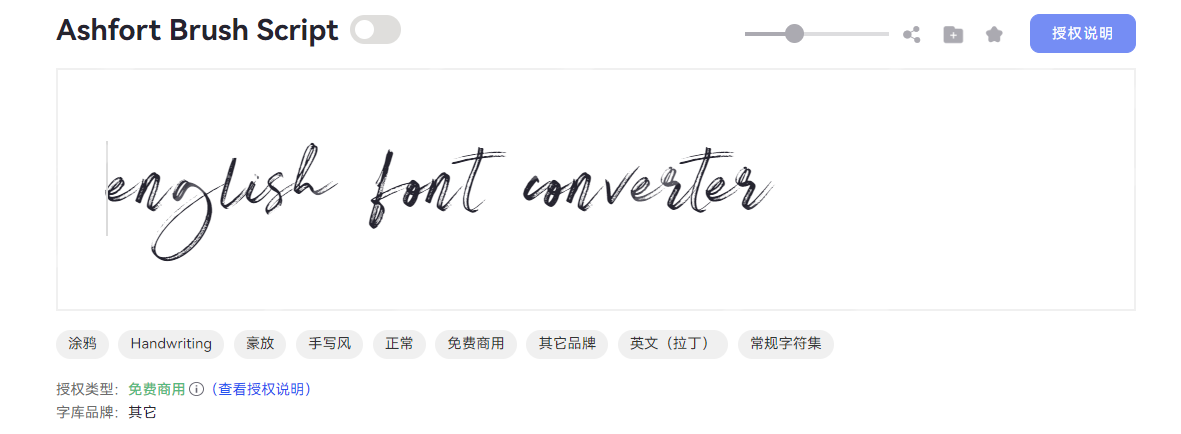
2.Montserrat——品牌 logo 设计
Montserrat 是一款极具设计张力的现代无衬线字体,以端庄简约的风格在视觉设计领域占据一席之地。它的字形结构尤为亮眼:整体形态修长,配合居中的重心与适中的中宫,在视觉上形成自然的平衡感与纵向延伸感,让文字排布更显通透。笔画边缘带有细腻的斜切处理,搭配粗实且均匀的线条,既强化了字体的力量感,又避免了厚重带来的压抑;而笔画头部的方头形态与断开式连接,则为字体注入了一定的秩序感。超粗的笔画特性使其在品牌 logo、标题设计等场景中极具表现力,传递了科技感和专业性。
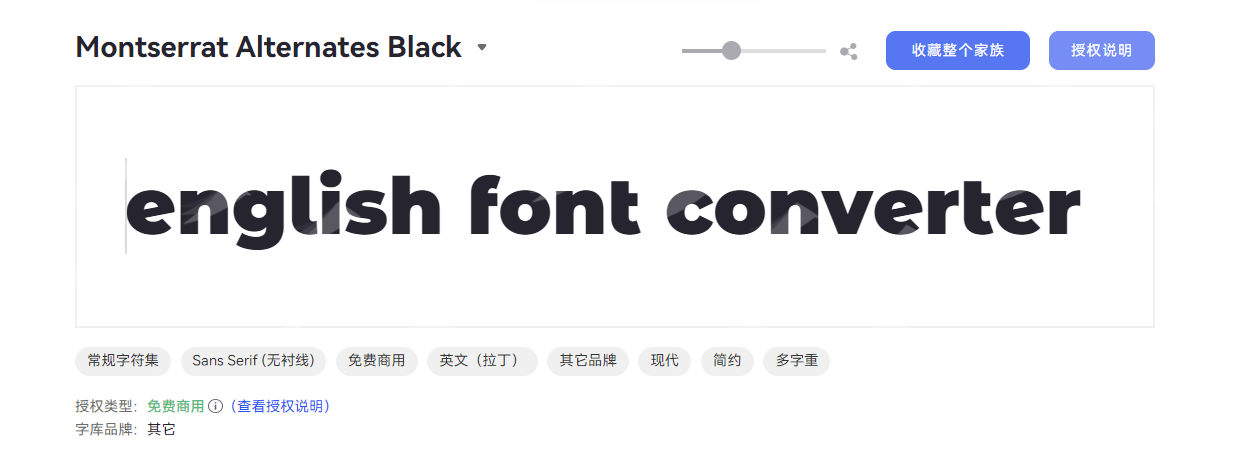
不管是你想要快速生成特色的英文字体,还是只想免费把默认字体转换为英文字体,字由都是不可多得的一个选择。它可以实现一键转换,而且可选的风格多种多样,版权也合规有保障。它不单单是一个英文转换器,它更是字体管理神器,很多延伸功能也对英文字体转换有一定的帮助,必要时刻也能给你一些字体设计的灵感哦。总的来说,想要高效完成英文字体转换,直接选择字由准没错,让你的设计更具独特魅力!